REGENERIERENDE FUßCREME von Hansaplast
Hansaplast hat eine neue Fußcreme herausgebracht. Sie wurde im Rahmen von dermatologischen Studien getestet. Ihre Formel habe sich zur Pflege bei extrem trockener Haut als äußerst wirksam und hautverträglich erwiesen. Bereits nach einer Woche Anwendungsdauer »erhöht die Creme die Hautfeuchtigkeit signifikant um 67 %« sagt Hansaplast. Weitere Informationen und Tipps gegen trockene Haut und Hornhaut findet ihr unter Harte Zeiten für Ihre Füße?
Was mir zu dem Produkt auf den ersten Blick einfällt:
- Hansaplasts Regenerierende Fußcreme enthält typografische Schadstoffe.
- Kann ich einer dermatologischen Studie trauen, wenn sich ein Schreibfehler durch alle Abteilungen eines Unternehmens schleicht?
- Hat die Einführung des Versal-Eszett zur Beliebigkeit bei der Benutzung des scharfen S geführt?
- Nein, die Schrift Myriad von Adobe enthält kein versales Eszett.
Das Hauptproblem liegt meines Erachtens in der Beobachtung, dass ganz viele einfach nicht mehr richtig hinsehen. Sonst müsste ihnen an der Form schon klar sein, dass das ß nicht zu den Versalien gehört und auch nicht passt. Vielleicht sollten wir mal wieder für eine Schule des Sehens plädieren und nicht für eine Schule des Setzens.
Deswegen haben sie ja auch REGENERIER-ENDE geschrieben.
aber ehrlich: Das Versal-Eszett macht keine bessere Figur in Versalschreibweise und sieht auch nach Gemeiner aus.
Sehe ich ähnlich … aber nur noch mal zur Orientierung: Aktuell ist das KEIN Versal-Eszett im Wort FUßCREME:
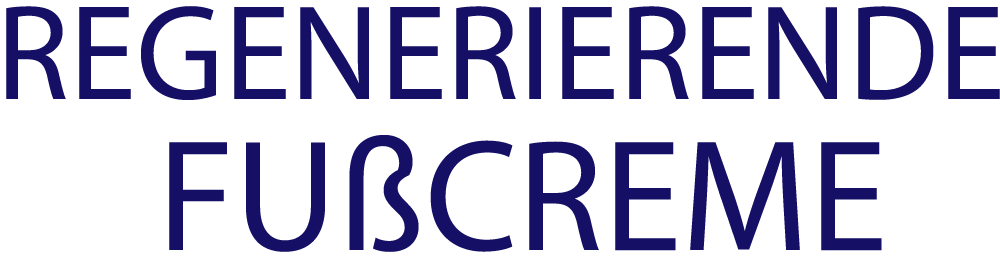
Diese Falschschreibungen haben in dem Marktsegment regelrecht Tradition.
Eucerin schreibt ebenfalls FUßCREME und Balea hat sogar verschiedene (falsche) Varianten: »Fuss Balsam« oder »FUß BALSAM«.
Recht hast du:
Dann wäre doch die FF Kievit inzwischen gleich eine nennenswerte Alternative! : )
Vielleicht sollte man dann fairerweise auch den Kollegen vom Duden eine Mail schicken. Denn dort steht, dass die abgebildete Schreibweise durchaus korrekt ist. So lange sich beim Duden nichts ändert, halte ich ein Umdenken bei der Masse für schwierig, da es doch die Referenz für Regelungen der deutschen Sprache ist.
Doof ist es trotzdem.
Duden — ß (Die letzten 3 Absätze)
Warum wird bei Satzfehlern immer auf die Firmen geschimpft und nicht auf die, die die Fehler machen, nämlich Grafikerinnen und Grafiker?
Außerdem: auch ein sogenanntes Versaleszett wäre ein Rechtschreibfehler, weil es das in den amtlichen Regeln nicht gibt.
Naja auf die Grafiker schieben wäre auch unfair. Die folgen letztendlich auch den Korrekturwünschen des Kunden. Ob Grafiker oder Firmen daran Schuld sind, kann man sowieso nicht festlegen.
Wir müssen auf die schimpfen, die die Fehler zu *verantworten* haben. Das sind ganz klar die Unternehmen, und nicht deren Grafiker — egal ob intern oder extern im Einsatz. Hauptverantwortlich ist in meinen Augen das Produktmanagement, bei dem sich die Grafik ihre Vorlagen absegnen lassen.
Ich kann gar nicht hingucken. Das brennt regelrecht in den Augen. Ich kann verstehen, dass FUSS komisch ausschaut und auch falsch gelesen wird. Aber einfach das gemeine ß als Versal-ß hinzustellen ist noch seltsamer. Leider setzt sich das Versal-ß nicht wirklich durch. Die angesprochene Problematik mit dem Duden ist sicher auch Teil der schleppenden Umsetzung seitens der Schriftgestalter.
@R::bert: Das schaut doch toll aus. Man hätte sich notfalls, wenn die Myriad nun mal die Hausschrift ist, sich das Versal-ß von der Kievit stibitzen können. *nichtschlagen*
Matthias
Aber wenns doch dermatologisch bestätigt ist!
philipp
UUPß! Da ist bei Baiersdorf wohl etwas schiefgelaufen. Leider kein Einzelfall, dabei ist’s im Grunde ganz einfach: Um gut zu entwerfen, brauchen wir Designer
1. Kreativen Sachverstand sowie das Selbstbewusstsein, ihn zu vertreten.
2. Verantwortungsvolle Ansprechpartner im Unternehmen, keine Duckmäuser am Ende der Nahrungskette.
Gutes Design ist Chefsache. Schlechtes Design ist Umweltverschmutzung.
Michael
Lektorinnen und Lektoren sollten sich das mit dem Versal-ß auch gut anschauen.
R::bert
@Jürgen
Da geht sogar noch mehr: http://next.fontshop.com/tryout/templates/blank/c2521dc2fa41
Na mal seh’n, wann die Milo dran ist. ;-)
DAS TOOL MACHT ÜBRIGENS SPAẞ. (Oh, oh – die Azuro ist auch noch im Betastadium ;-D)
Übrigens: Die Duden, nicht mehr der.
manuel
kommt sowas?
Guru
Gibt es noch private Verlage? Oder gehören die schon alle internationalen Anlegern, Kommissionen und so weiter und so fort? Egal!
Es macht nämlich keinen Unterschied, ob ein privater Verlag oder eine internationale Kommission – wegen Geltungswahnes – eine in sich gewachsene Sprache zerstört.
Varianten in T-Star
Man kann nicht den Anwendern die gesamte Schuld geben, wenn Fontdesigner das Problem mit
calt
verhindern könnten.